Font Designer Ben Kiel und Jesse Ragan, die Miteigentümer von XYZ Type, bauen weder Gartenbrunnen noch gießen sie Metall (zwei weit verbreitete Berufsvorurteile, denen die beiden begegnen). Stattdessen sind sie flotte 40-Jährige, die ihren eigenen Laden gründeten, nachdem sie sich 2005 auf der TypeCon NYC kennengelernt und gemeinsam Karaoke gesungen hatten.
Ben kümmert sich um die Finanzen von XYZ, erstellt Fonts und lehrt an der Washington University in St. Louis, MO; Jesse schreibt Texte und entwirft Schriften von seinem Haus in Beacon, NY. Die beiden lieben ihre großen Kunden (u. a. Aldo Shoes), verzahnen ihre Talente (obwohl sie in verschiedenen Staaten und Zeitzonen leben) und hassen den Schrift Jargon (verwenden ihn aber trotzdem).
MyFonts (MF): Was passiert derzeit bei XYZ? Sind irgendwelche großen Projekte im Gange?
Ben Kiel (BK): Wir starten am Freitag eine neue Webseite , also sind wir ein bisschen in Eile.
MF: Herzlichen Glückwunsch! Was ist der Grund für die Einführung?
BK: Dummheit - nur ein Scherz! Unsere neue Website stammt von GrayBits - sie haben das Design und die Entwicklung übernommen - und ermöglicht es uns, mehr Optionen für Lizenzierung anzubieten. So können wir große Familien auf eine Art und Weise präsentieren, wie wir es vorher nicht konnten.
Jesse Ragan (JR): Und variabel Fonts!
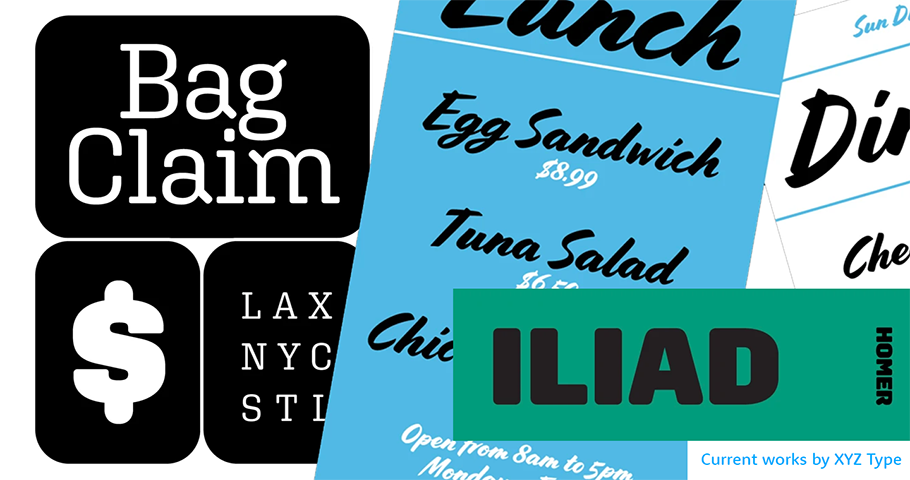
MF: Sprechen Sie über Über Font Familien, wenn Sie so wollen. Sind das Familien mit mehreren Elternteilen? Ein-Eltern-Familien?
BK: Wir heißen alle Familien willkommen!
JR: Ich ziehe es vor, Worte wie "Geschwister" oder "Eltern" oder "Cousin" zu vermeiden, wenn ich Fonts beschreibe. Aber "Familien" ist ein offizieller Begriff im Schriftdesign.
BK: Es bedeutet einfach eine Sammlung. Wir haben also unseren Cortado Font - den die Leute aus offensichtlichen Gründen gerne für Kaffee verwenden - zusammen mit Jesses bevorstehendem Elevator und Escalator Schriften, den wir bald online stellen werden. Und wir haben Fonts in zukünftigen Untersammlungen, die kondensierte, komprimierte, normale und breite Stile umfassen. Hätten wir versucht, all das zu der alten Webseite hinzuzufügen, hätten wir eine Auswahlliste, die sich einfach auflöst! Wir sind also für die Zukunft gerüstet.
MF: Um noch einmal auf die Familiensache zurückzukommen: Warum mögen Sie diesen Begriff nicht?
JR: Als wir anfingen, uns mit Werbetexten zu befassen, hatten wir absurde Diskussionen, wie zum Beispiel: Ist Font eher ein Geschwisterchen oder ein Cousin? Die Analogien ergeben keinen Sinn! Es scheint also albern, sie weiterhin zu verwenden.
BK: Es gibt schon genug dumme, fachsprachliche Dinge im Schriftdesign. Wir müssen es nicht noch verwirrender machen.
MF: Apropos herstellen, was ist eines der ersten großen Dinge, die Sie zusammen geschaffen haben?
JR: Vor Jahren arbeitete ich an einem Kundenprojekt mit einer sehr knappen Frist. Wir mussten diese aufwändige OpenType-Schrift Font erstellen, die schließlich zu Cortado wurde. Es war nicht nur ein Skript Font, das ich noch nie zuvor gemacht hatte, sondern es brauchte auch OpenType-Funktionen für eine Menge komplexer Ersetzungen. Ben hatte Erfahrung mit beidem. Also habe ich ihn gebeten, mit mir daran zu arbeiten.
Sobald Cortado existierte, haben wir es in ein Einzelhandels-Produkt umgewandelt, weil es nicht exklusiv für den ursprünglichen Kunden war: Aldo Shoes. Wir haben es ohne einen Foundry Namen. Aber danach wussten wir, dass wir gut zusammenarbeiten und beschlossen, unser eigenes Unternehmen zu gründen.
MF: Jetzt, wo die Schreibschrift nicht mehr in der Schule gelehrt wird, haben Sie das Gefühl, dass Sie mit der Entwicklung der Schreibschrift eine Art von Retro sind?
JR: Gott, ich hoffe nicht!
BK: Das Wort "Retro" erregt die Gemüter. Aber, nein. Cortado ist nicht wirklich eine kursive Schrift. Es ist eine sehr lockere, nicht-traditionelle Pinselschrift, nicht das, was ein Schildermaler machen würde. Sie basiert auf der Pinselschrift von Cecilia Carlstedt, einer Illustratorin.
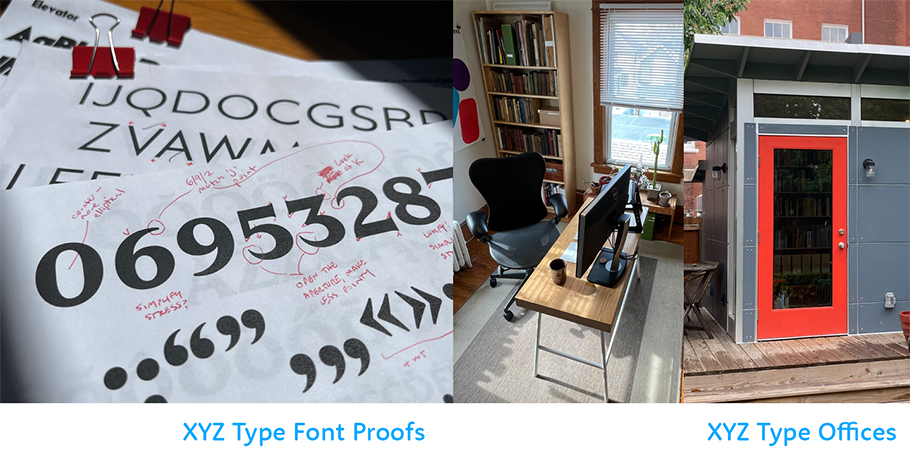
MF. Warum ist "Retro" ein Schimpfwort? Was suggeriert es?
BK: Retro ist etwas, das in Designkreisen oft als Pejorativ verwendet wird. So nach dem Motto "Oh, das ist einfach nur retro". Jesse und ich schauen uns gerne die Geschichte an, aber immer wenn wir eine digitale Version von etwas schaffen, rücken wir es in ein neues Licht für den modernen Gebrauch.
Allerdings kann alles, was wir tun, ein Rückblick sein, den man bei Schrift nicht ganz vermeiden kann. Zum Beispiel: ein "a" ist ein "a". Man kann ein "a" nur so lange völlig anders zeichnen, bis die Leute aufhören zu erkennen, dass es ein Buchstabe ist.
JR: Auch "Retro" legt das Design in eine Schublade, die für einen bestimmten Zweck bestimmt ist. Doch woher die Inspiration für das Design kommt - Cortado hat eine gewisse Ästhetik aus der Mitte des Jahrhunderts - diktiert nicht notwendigerweise, wie es verwendet werden soll. Wir hoffen, dass unsere Produkte nicht in der Zeit stehen bleiben, sondern in einen Kontext gestellt werden können, der etwas völlig Neues schafft.
BK: Dass wir die Schriften machen. Sie sind unsere Interpretation von Formen und sie sind unsere Persönlichkeit, ausgedrückt durch Buchstaben. Das mag - oder auch nicht - der Geschmack sein, nach dem jemand sucht. Aber wir machen die Dinge, die wir gerne machen, und wir haben einen Raum mit dem Foundry um das zu tun.